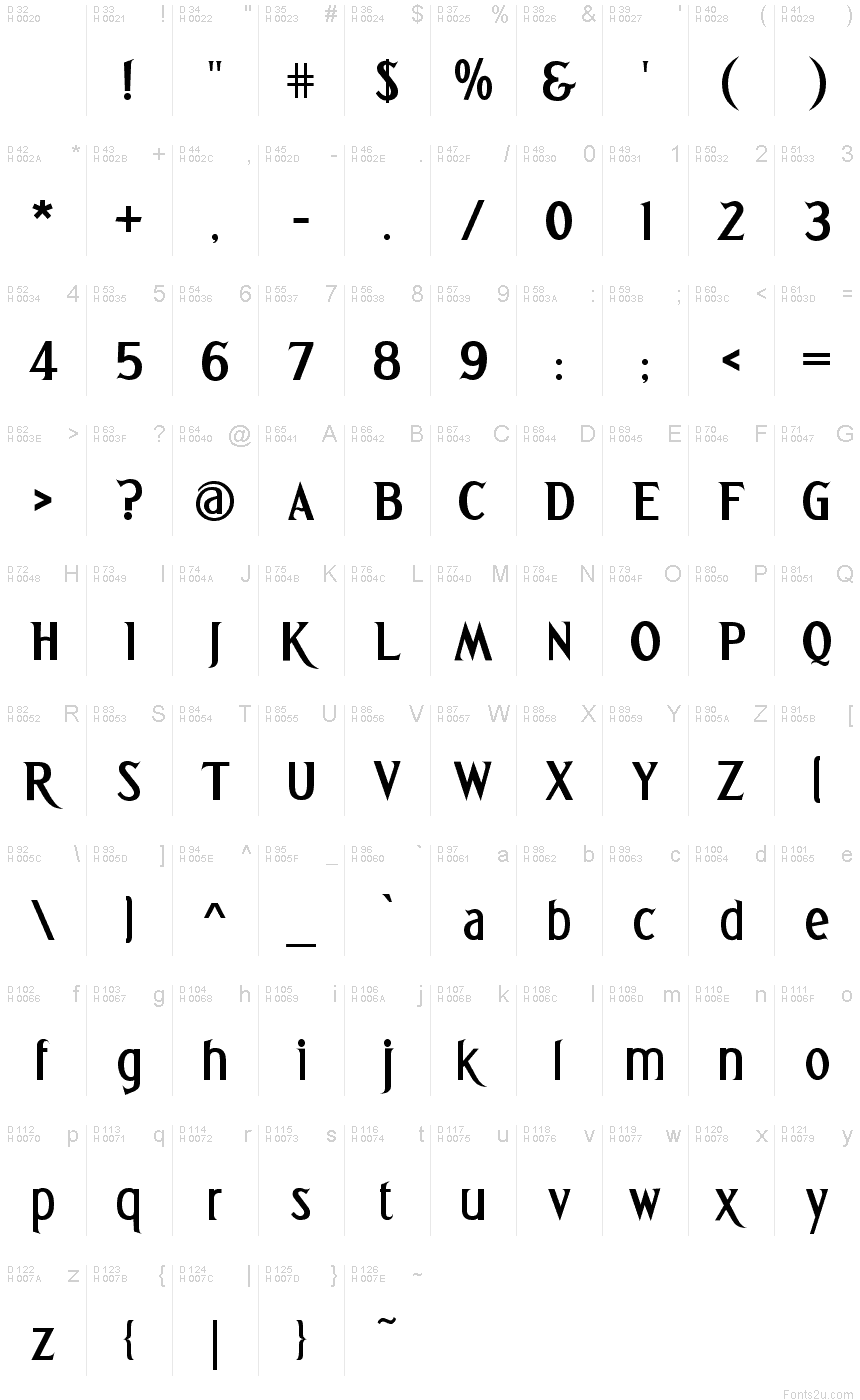
Greetings Bold
Greetings Bold od Keith Bates to darmowy, kontrastowy krój szeryfowy o żwawym, nieco teatralnym charakterze. Litery łączą wysokie, czyste pionowe kreski z ostro zakończonymi szeryfami i zwężonymi łukami, co nadaje całości formalny, lecz żywy, a nie sztywny ton.
Ten darmowy font świetnie sprawdzi się na okładkach książek, w nagłówkach magazynów, w brandingu butików, na plakatach eventowych i planszach tytułowych, gdzie potrzeba klasycznego głosu z nutą dramatyzmu. Dobrze sprawdza się też w krótkich cytatach lub inicjałach, ponieważ ostro zarysowane łączenia i zwarte krzywizny nadają nawet kilku literom wyrazisty, literacki sznyt.